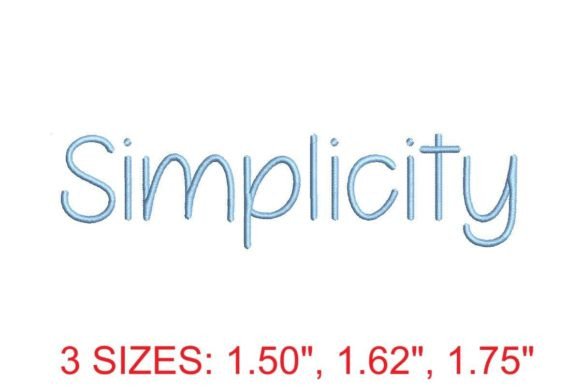
Simplicity Embroidery Font
Ультра‑популярный анализ шрифта «Simplicity Embroidery Font»
Ищете идеальный шрифт для вышивки, который подчеркнет элегантность и простоту ваших работ? «Simplicity Embroidery Font» — это надёжный выбор для всех, кто ценит качество и стиль. Этот шрифт создавался с тщательной точностью, чтобы вы могли воплотить любые идеи в вышивке, будь то персонализация одежды, монограммы или просто декоративные элементы.
Преимущества шрифта Simplicity Embroidery Font
- Полный набор букв — 156 символов, включая заглавные и строчные, с подробной таблицей размеров и количества стежков.
- Идеально для любого уровня — от начинающих до профессионалов; легко встраивается в проекты любого сложности.
- Экономия времени — готовые стили позволяют быстро подготовить макет и перейти к работе.
- Высокий эстетический уровень — чистый, лаконичный дизайн, который добавляет изысканности даже самым простым изделиям.
«Simplicity Embroidery Font» — это ваш ключ к созданию стильных, ярких и безупречных вышивок. Поднимите свой уровень мастерства и добавьте в свои изделия изящества без лишних усилий.